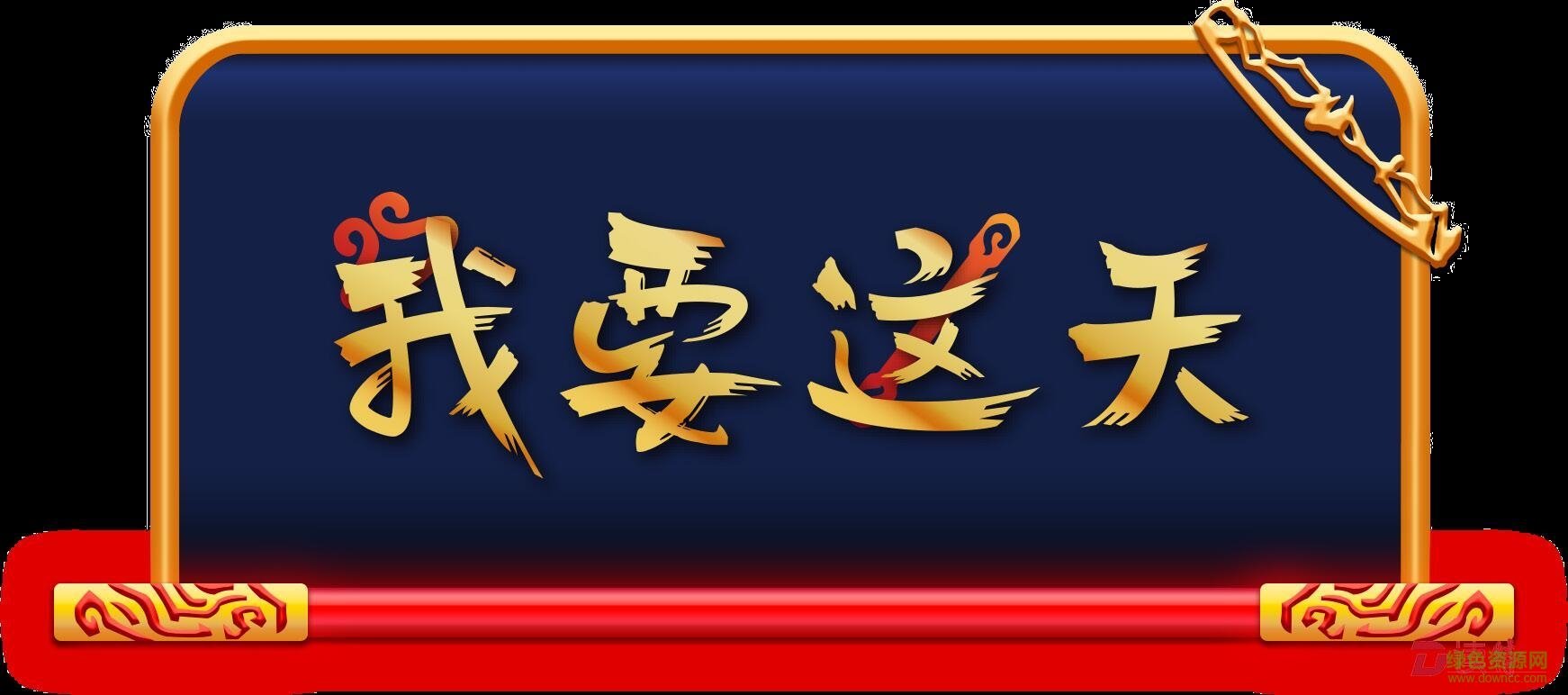
方正悟空体是方正字迹推出的一款新字体,字迹简单随意,蕴含着凌厉的气势和恣意的风采,蓝色的背景显得光芒万丈和唯我独尊,喜欢的朋友就来绿色资源网抢先体验吧!
“方正悟空体”的设计者--方正手迹设计团队介绍道,孙悟空的热血、洒脱、有情有义,深深感染着数代中国人,此次希望借由文字,将这个角色的艺术魅力持续延伸。
“方正悟空体”的设计风格取自孙悟空桀骜不驯的人物性格,并将其设计为彩色字体。黄色的主体字与充满激情斗志的红色挂件,深蓝色背景搭配相得益彰,体现了悟空与其命运抗争的希望与热血燃烧的激情。